Stellen Sie sich vor, Sie schreiben einen fesselnden Roman, wählen aber eine so störende Schriftart, dass die Leser schon nach der ersten Seite fliehen.
Die Schriftart ist der unbesungene Held der Lesbarkeit, bei der ein falsch platzierter Serif die Welt in Benutzerbindung bedeuten könnte.
In der geschäftigen Welt der Android-Geräte dienen die besten Schriftarten für Android nicht nur als einfacher Text, sondern als Tor zur Bedienbarkeit, Zugänglichkeit und diesem unverzichtbaren ästhetischen Reiz.
Dieser Artikel schält die Schichten der mobilen Typografie ab und führt Sie zum Typeface Olympus. Vergessen Sie systemeigene Standardschriften; es ist Zeit für ein typografisches Upgrade, das Persönlichkeit ausstrahlt, aber Lesbarkeit auf allen Bildschirmgrößen flüstert.
Am Ende dieses Artikels werden Sie fließend in der Kunst der Schriftanpassung sein, von den Feinheiten der Schriftdateien für Android bis hin zur Balance von Schriftgewicht und -stil.
Tauchen Sie ein in einen kuratierten Schatz von Schriftarten, der Ihre Android-Oberfläche von trist zu fantastisch verwandelt und sicherstellt, dass Bildschirmlesbarkeit und dynamische Textskalierung harmonisch in Ihren App-Designs leben.
Bereit? Lassen Sie uns über Schriftarten sprechen!
Die besten Schriftarten für Android-Apps
| Schriftname | Designer / Gießerei | Erscheinungsjahr | Anzahl der Stile | Eigenschaften |
|---|---|---|---|---|
| Roboto | Christian Robertson / Google | 2011 | 12 (6 Gewichte + Kursiv) | Modern, geometrisch, vielseitig, sehr lesbar |
| Open Sans | Steve Matteson / Google | 2011 | 10 (5 Gewichte + Kursiv) | Humanistisch, sauber, freundlich, für Web und Mobil optimiert |
| Lato | Łukasz Dziedzic / tyPoland | 2010 | 10 (5 Gewichte + Kursiv) | Halbrund, professionell, harmonisch |
| Montserrat | Julieta Ulanovsky / Google | 2011 | 36 (9 Gewichte in aufrecht und kursiv) | Urban, geometrisch, zeitgenössisch |
| Source Sans Pro | Paul D. Hunt / Adobe | 2012 | 12 (6 Gewichte + Kursiv) | Humanistisch ohne Serifen, neutral, für UI optimiert |
| Noto Sans | 2020 | Zahlreiche Gewichte und Stile | Zielt auf universelle Sprachabdeckung ab, sauber | |
| Raleway | Mehrere Designer / The League of Moveable Type | 2012 | 18 (9 Gewichte + Kursiv) | Elegant, stilvoll, großartig für Titel und Überschriften |
| PT Sans | Alexandra Korolkova, Olga Umpelova, Vladimir Yefimov / ParaType | 2009 | 8 (4 Gewichte + Kursiv) | Humanistisch, offene Formen, unterstützt Kyrillisch |
| Ubuntu | Dalton Maag / Canonical Ltd. | 2011 | 8 (4 Gewichte + Kursiv) | Einzigartig, technisch orientiert, Ubuntu-Markenidentität |
| Merriweather | Sorkin Type | 2012 | 8 (4 Gewichte + Kursiv) | Serifenschrift, zeitgenössisches Design, lesbarer Text |
| Nunito Sans | Vernon Adams, Jacques Le Bailly / Google | 2017 | 14 (7 Gewichte + Kursiv) | Rund, ausgewogen, geeignet sowohl für Anzeige als auch Text |
| Poppins | Jonny Pinhorn, Ninad Kale / Google | 2014 | 18 (9 Gewichte + Kursiv) | Geometrisch, modernistisch, freundlich |
Google’s Roboto Schriftart
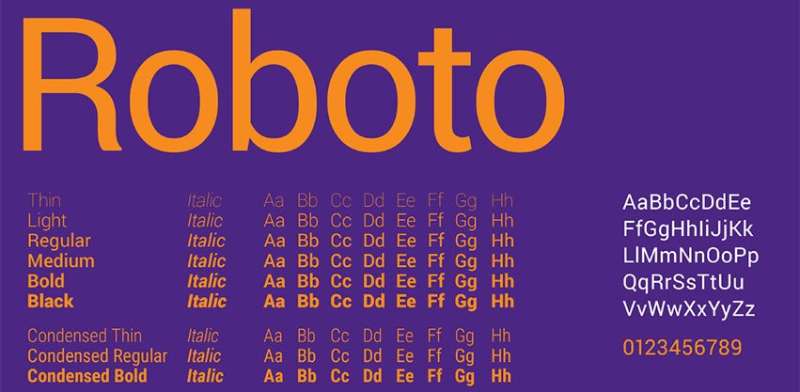
Beginnen wir mit einem Klassiker: Googles Roboto-Schriftart. Diese ist wie das Brot und Butter der Android-Typografie. Sie ist überall zu finden, und das aus gutem Grund. Mit einem Fokus auf Mobile-UI-Design bietet Roboto eine unvergleichliche Mischung aus Modernität und Zugänglichkeit. Sie ist wie jener Freund, der cool ist, ohne es zu versuchen.
Sie haben Roboto wahrscheinlich schon in verschiedenen Android-Schnittstellen gesehen. Sie hat ein mechanisches Gerüst, aber die Formen sind super freundlich und offen. Diese Schrift ist nicht nur ein hübsches Gesicht; es geht um digitale Bildschirmlesbarkeit. Ob es sich um eine schnelle Benachrichtigung oder ein langes Lesen handelt, Roboto hält alles klar und stilvoll.
Open Sans
Als nächstes kommt Open Sans. Diese Schrift ist der Liebling der Leute. Denken Sie an sie als den freundlichen Nachbarn unter den Schriftarten — bekannt, vielseitig und oh-so-lesbar. Sie hat diese humanistischen Qualitäten, die Text warm und einladend machen.
Optimiert für digitale Bildschirme ist Open Sans nicht nur für Android-Apps geeignet. Sie wird überall im Web verwendet. Das Beste daran? Sie ist ein Alleskönner. Von knackigen Überschiften bis hin zu detailliertem Inhalt, Open Sans meistert es mit Leichtigkeit. Sie ist wie das Schweizer Taschenmesser in der Welt der besten Schriftarten für Android.
Lato
Nun sprechen wir über Lato. Sie ist das stilvolle Cousin in der Schriftfamilie. Lato bringt ein zeitgemäßes Flair mit sich und balanciert Professionalität mit einer freundlichen Note. Seine Lesbarkeit ist erstklassig, was es sowohl für Android als auch für Webinhalte zu einem Hit macht.
Es gibt einen emotionalen Aspekt bei Lato, den man nicht ignorieren kann. Es ist nicht nur eine Schriftart; es ist eine Designaussage. Von Tech-Blogs bis hin zu stilvollen Apps hat Lato seine Nische wunderschön geschnitzt. Es ist diese perfekte Mischung aus Geschäft und persönlichem Flair.